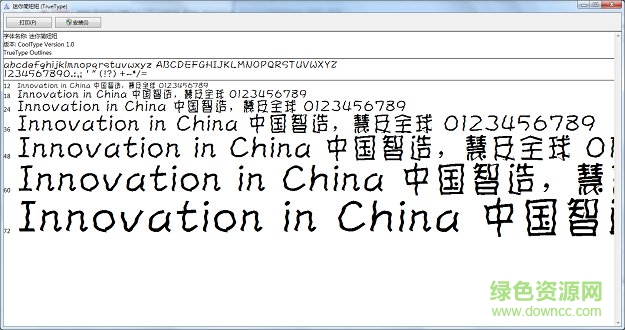
迷你簡妞妞字體是一款提供給需要進行文字編輯,媒體創(chuàng)作用戶免費使用的字體文件,通過進行安裝使用用戶能夠為文字各類風(fēng)格與藝術(shù)效果,創(chuàng)作出比較舒適的字體形式!
迷你簡妞妞的字體風(fēng)格是帶有扭曲效果的字體樣式,給你一種全新的字體效果,快來體驗吧!